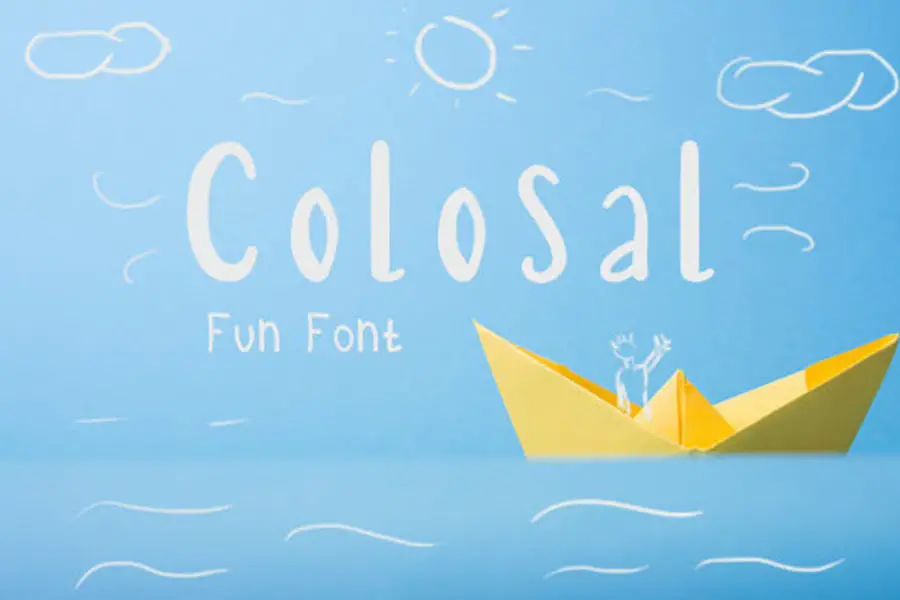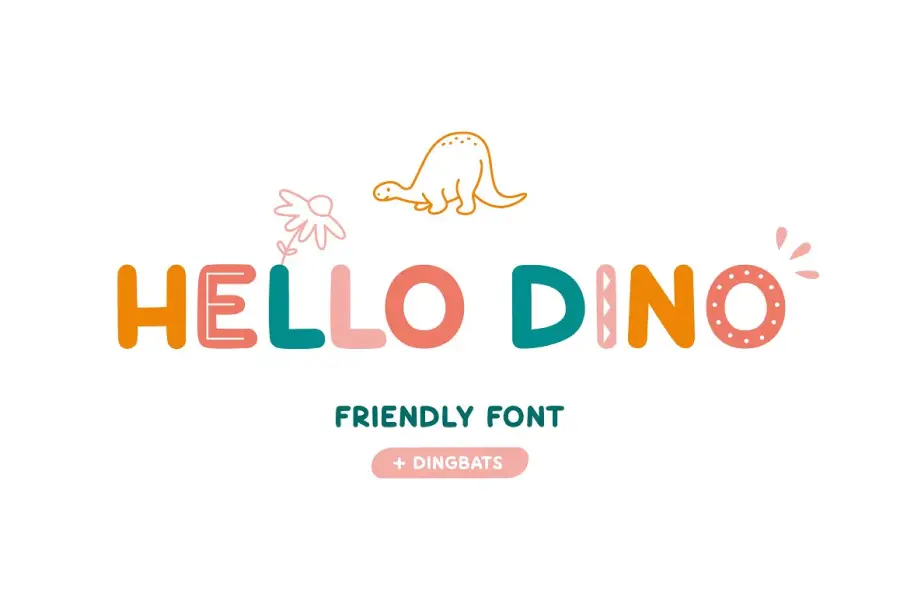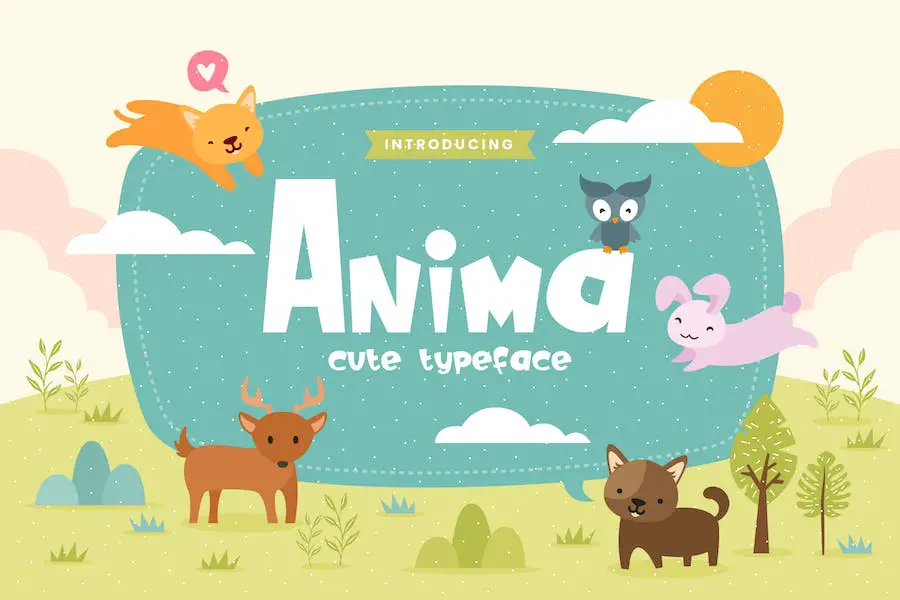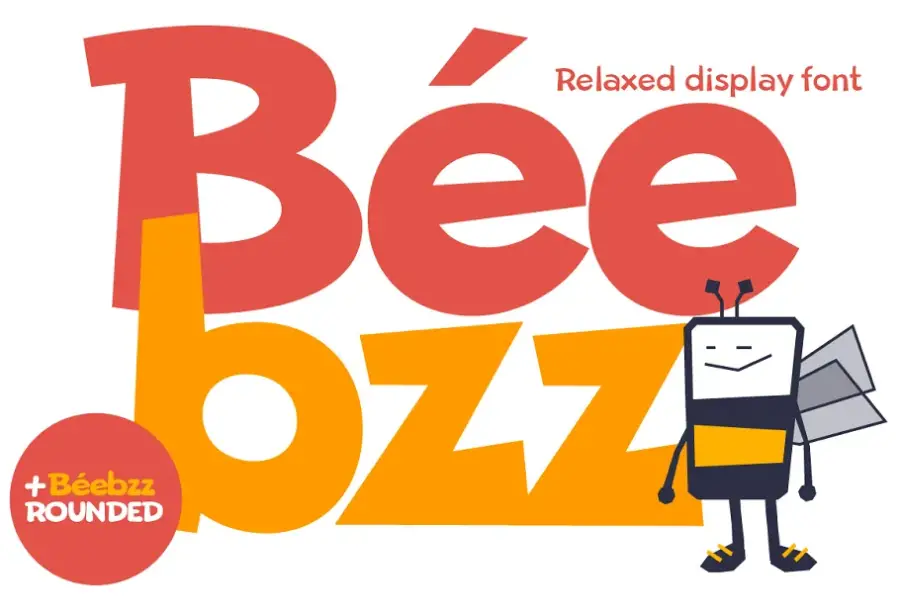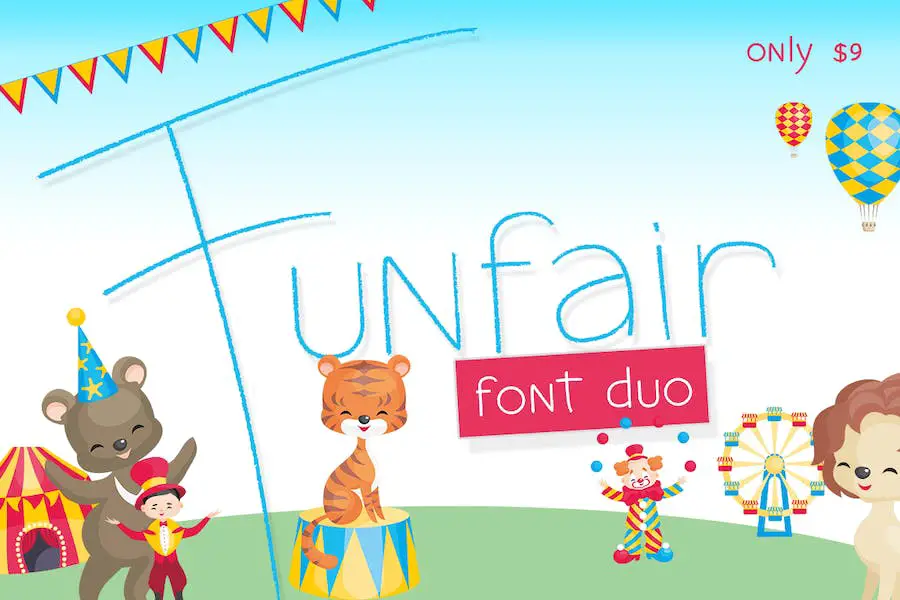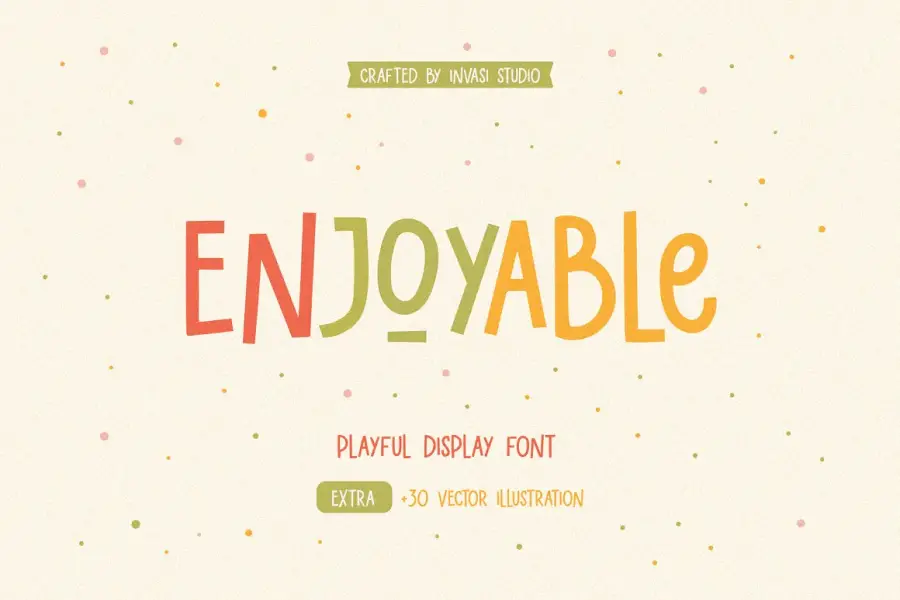
Sus proyectos se destacarán con fuentes divertidas. No importa si está diseñando ilustraciones, gráficos de sitios web o simplemente quiere un toque extra en su texto, hay una fuente que funcionará. Estas son algunas de las fuentes divertidas más populares y creativas de la actualidad.
¡Sé creativo con tu texto con estas fuentes divertidas!
Las mejores fuentes premium divertidas
Ya sea que esté creando un logotipo, diseñando un póster o creando un sitio web, encontrar la fuente correcta es esencial. Las fuentes premium pueden llevar sus diseños al siguiente nivel, brindándole una variedad de estilos tipográficos únicos para elegir. Hemos reunido algunas de las fuentes premium más populares y divertidas disponibles, para que no tengas que pasar horas buscando el tipo de letra perfecto.
¡Prepárate para agregar algo de personalidad a tu proyecto de diseño y libera el potencial de tu texto con estas divertidas fuentes premium!
dulce y tonto
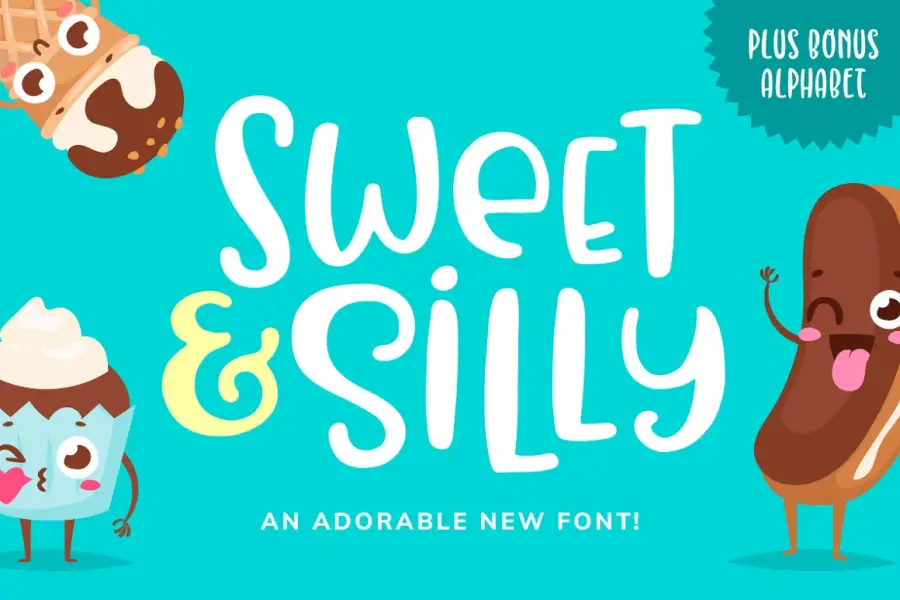
Este divertido diseño hace que Sweet & Silly sea la elección perfecta para todo, desde tarjetas de cumpleaños hasta publicaciones en redes sociales. Sus alegres letras harán que tu trabajo sea extravagante y divertido. Y con tantos estilos, puedes obtener exactamente lo que quieres.
Sweet & Silly es una fuente única que se destaca sin quitarle el aspecto general cuando trabajas en proyectos sutiles. El estilo de escritura a mano garantiza que su mensaje se destaque sin quitarle el aspecto general. Además, tiene muchas formas y tamaños, para que puedas ser creativo.
hola divertido
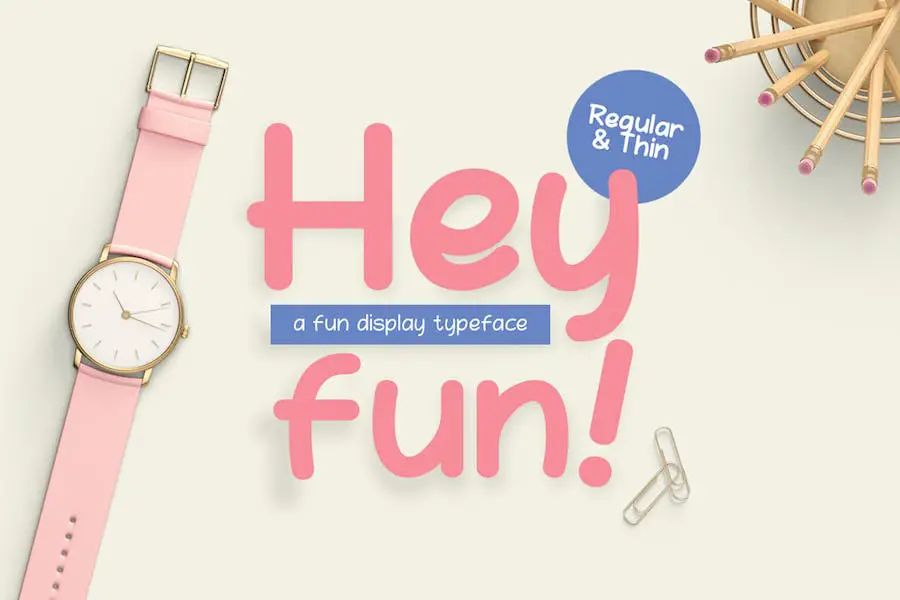
Puede usar Hey Fun para logotipos, marcas, tarjetas de felicitación, carteles y más. Viene en dos estilos diferentes: regular y delgado. También te da la posibilidad de usar fuentes divertidas.
Hey Fun es fácil de leer y brinda una apariencia única a sus proyectos. Su tema alegre le da a los proyectos una sensación alegre, mientras que sus líneas limpias mantienen el enfoque en su contenido. Además, sus divertidas curvas le dan personalidad a la fuente y la hacen destacar entre otras fuentes.
Tutti Frutti
Tutti Frutti es un tipo de letra en negrita escrito a mano súper divertido y juguetón que se puede usar en una variedad de proyectos de diseño. Es perfecto para encabezados, diseños de folletos, tarjetas de felicitación, empaques de productos, portadas de libros, citas impresas, logotipos, diseños de ropa y portadas de álbumes.
Ya sea que esté creando un logotipo o un proyecto de impresión, este estilo de letras único hace que se destaque fácilmente. Las letras son fáciles de leer y distintivas, y se sienten vivaces, por lo que cualquier diseño puede destacarse. Los diseñadores podrán ser creativos con esta fuente, ya que está disponible en una variedad de pesos y anchos.
sagobi
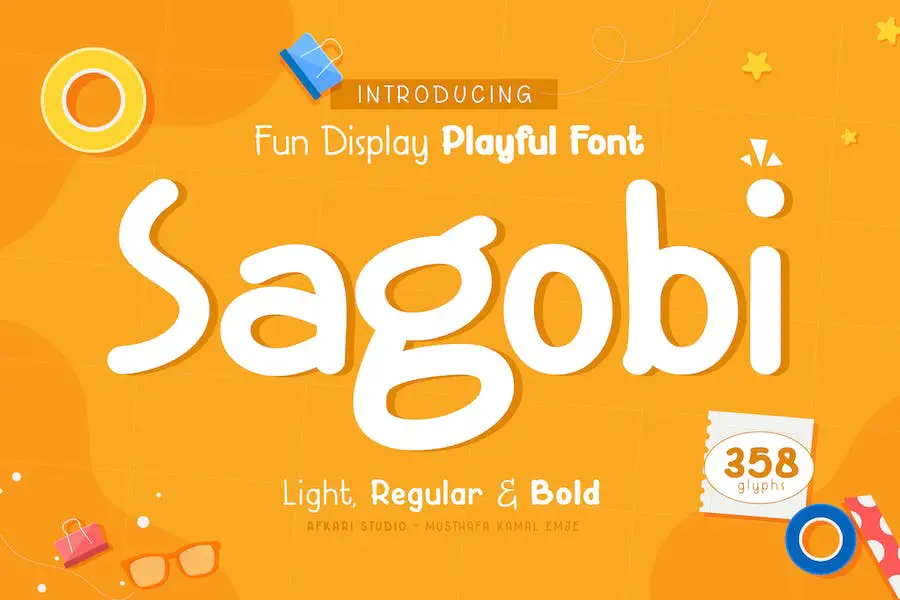
Sagobi es una fuente de visualización divertida y lúdica creada con tipografía manuscrita natural. Viene en tres pesos diferentes: ligero, normal y audaz. Con Sagobi, puedes convertir cualquier idea creativa en una verdadera obra de arte.
La fuente es adecuada para muchos usos, desde tarjetas de felicitación e invitaciones hasta carteles, ropa para bebés, portadas de libros y citas. Los logotipos, las presentaciones y los titulares también lucen geniales con el divertido diseño de Sagobi. El estilo escrito a mano le da a sus diseños un toque personal que se destaca entre la multitud.
Fandango
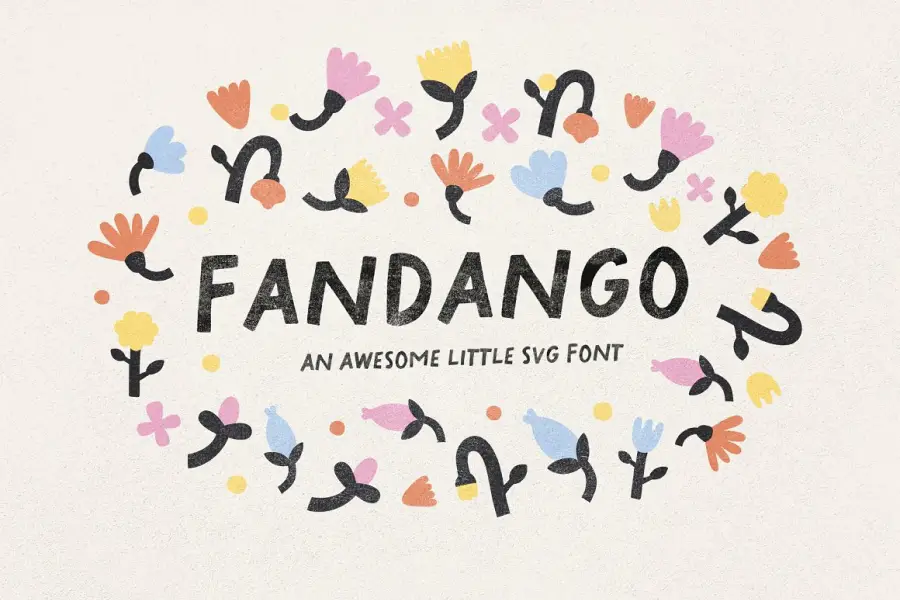
Fandango es una fuente SVG escrita a mano en mayúsculas que es perfecta para hacer una declaración. Esta fuente presenta texturas sutiles, lo que la hace ideal para crear citas en negrita, marcas divertidas, libros para niños y tarjetas de felicitación peculiares. Fandango se puede usar fácilmente con Photoshop CC 2017 o Illustrator CC 2018 y versiones posteriores, y también se proporciona una versión normal si no tiene esos programas.
Fandango se ganará su corazón: con su diseño texturizado, características inteligentes y capacidades SVG, seguramente hará que sus cosas se destaquen entre la multitud.
Diversión de invierno Dingbat
'Winter Fun Dingbat' es un sencillo garabato de temática invernal con 62 símbolos incluidos. Perfecto para diseños de logotipos, adornos y otros proyectos, 'Winter Fun Dingbat' le dará a su trabajo un poco más de vida. Es perfecto para aquellos que quieren agregar un toque invernal a su trabajo, pero que lo mantengan simple y minimalista. Con su estilo único, este dingbat hará que cualquier proyecto se destaque del resto.
Además de facilitar la combinación con otros elementos, el diseño simple facilita el diseño y la creación de logotipos impresionantes. 'Winter Fun Dingbat' es perfecto si eres un diseñador gráfico que busca una nueva fuente para su cartera o un aficionado creativo que busca mejorar su trabajo.